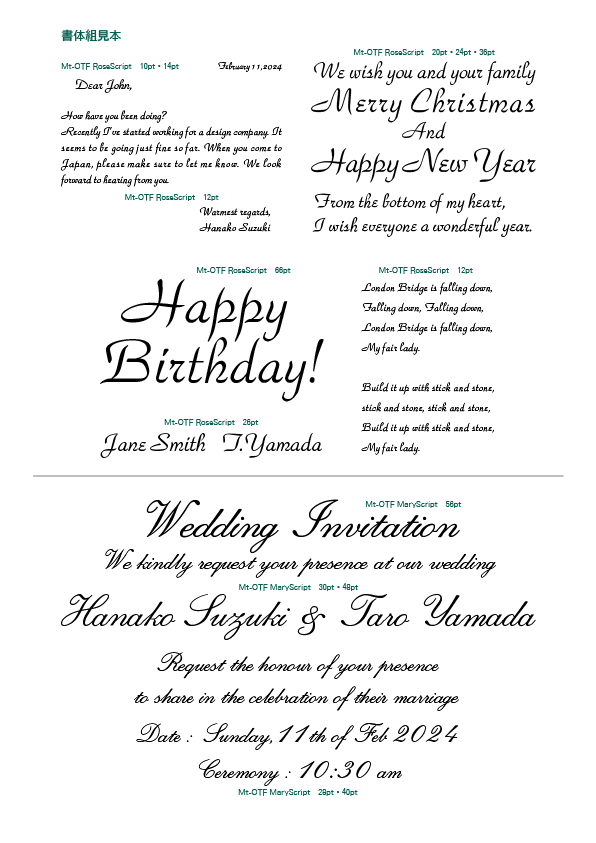
モトヤ欧文書体デザインコレクション
欧文書体デザインコレクションは、文章の雰囲気に合わせて欧文を変更できるように厳選した12種類の欧文書体です。個性的なデザインの欧文書体が、文章のイメージを様々に彩ります。
Mt-OTF Aqua Lt/Md/Bd
スラブセリフ(セリフとストロークが同じ太さ)を持つ書体で、文章に力強い印象を付与できます。
Mt-OTF Cymbal Md/Bd
文字の端に小さなセリフを持つ書体で、文章に高級感と上品な印象を付与できます。
Mt-OTF Flat Lt/Md/Bd
幾何学的な形状で造形されたサンセリフ体で、シンプルで癖がなく、幅広い場面で使用できます。
Mt-OTF BloomScript Rg/Bd
ブラシで書いたようなカリグラフィーが特徴的な筆記体で、文章に躍動感を付与できます。
Mt-OTF RoseScript
しなやかな曲線を持つスタイリッシュな筆記体で、文章に上品な印象を付与できます。
Mt-OTF MaryScript
羽根ペンで書いたようなカリグラフィーが特徴的な筆記体で、文章に優雅な印象を付与できます。
OpenTypeフォント機能を搭載
「モトヤ欧文書体デザインコレクション」の各書体には、OpenTypeフォント機能が搭載されており、Adobe InDesignやAdobe Illustratorなどの対応アプリケーションで、「合字」や「カーニング」といった機能を使用することができます。
合字機能
分数などの特定の文字の並びに対して、それらを組合せた単一の文字に置換する機能に対応しています。
カーニング
特定の文字同士が並んだ際に、体裁が良く見えるように自動的に字間を調整する機能に対応しています。